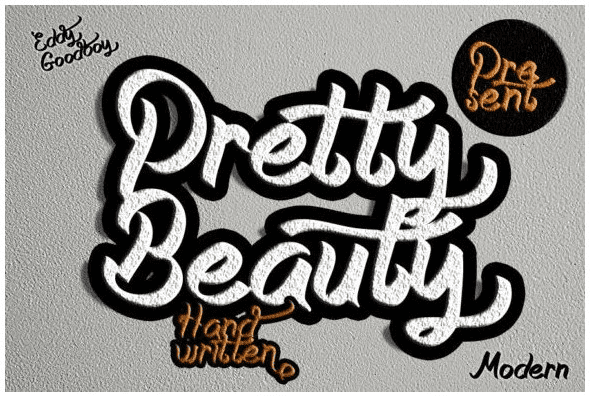
Название: Pretty Beauty Font
Pretty Beauty - это сладкий и скорописный рукописный шрифт.
Этот модный и толстый шрифт с густым шрифтом будет великолепно смотреться на разнообразных дизайнерских идеях.
Он добавит радостный и романтичный штрих в каждый из ваших проектов!
Название: Pretty Beauty Font
Pretty Beauty - это сладкий и скорописный рукописный шрифт.
Этот модный и толстый шрифт с густым шрифтом будет великолепно смотреться на разнообразных дизайнерских идеях.
Он добавит радостный и романтичный штрих в каждый из ваших проектов!